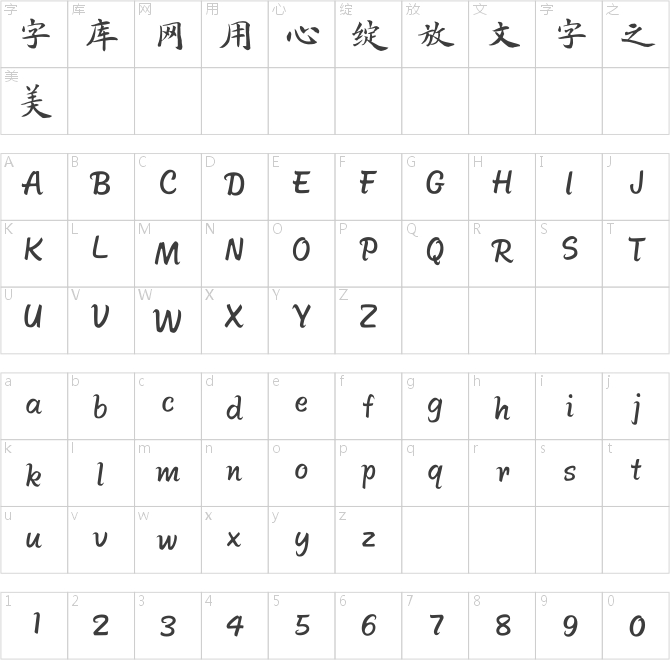
方正字跡-王燕民楷書簡 詳情頁
《方正字跡-王燕民楷書》是由中央電視臺資深美術(shù)指導(dǎo)、國家一級美術(shù)師、著名書畫家王燕民先生書寫創(chuàng)作的。字體以清麗雅正為主旨,結(jié)體嚴(yán)謹(jǐn)整飭,筆畫舒展勁秀。骨氣峻朗,平和靜穆,散發(fā)出蘊(yùn)藉涵泳的書卷氣息。適應(yīng)面較廣,最宜溫潤和諧的語義表達(dá)。